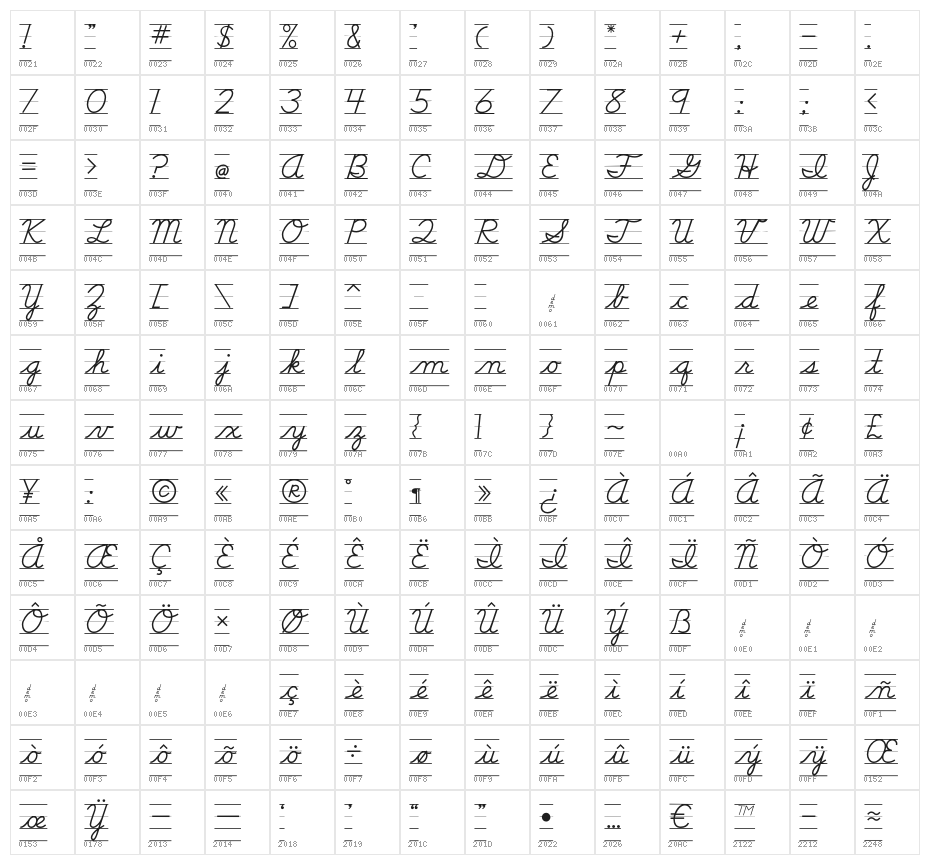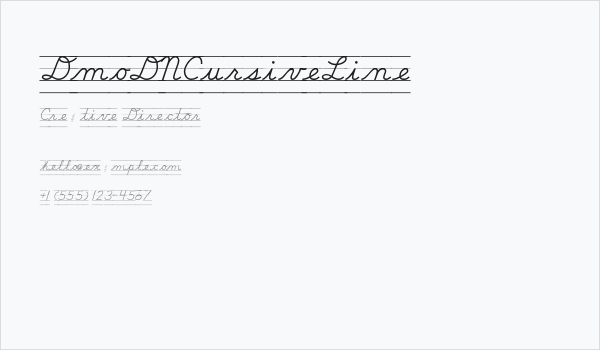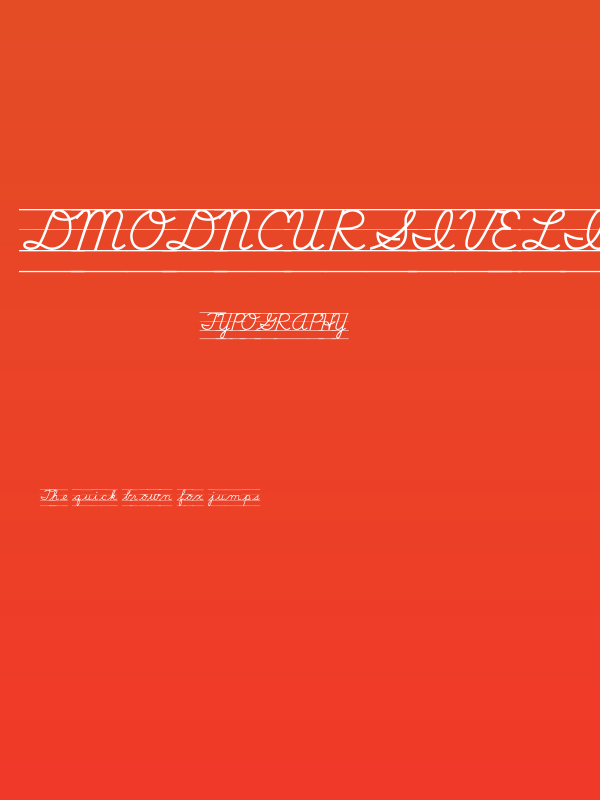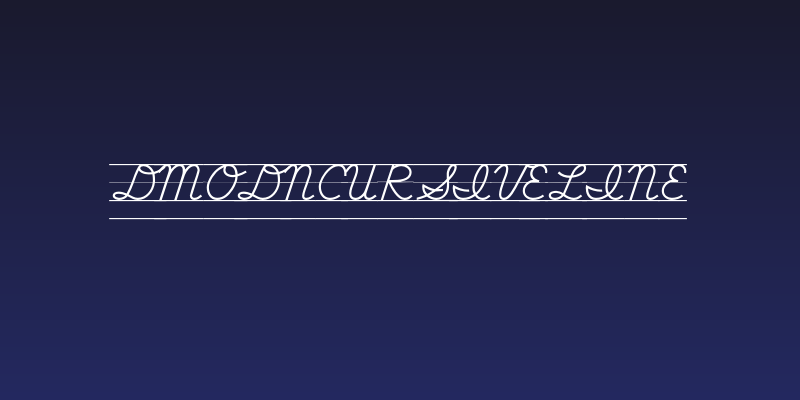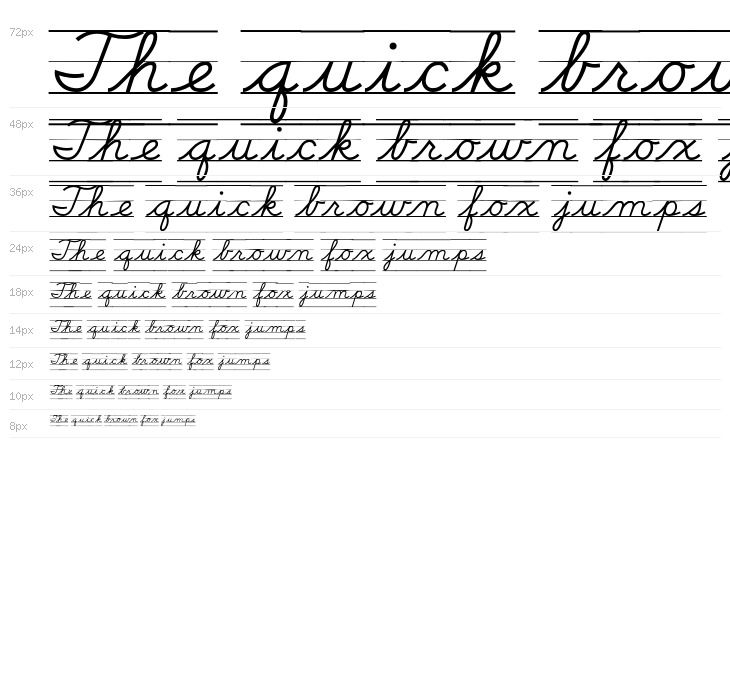
DmoDNCursiveLine Font
| Caso d'uso | Logos, Invitations, Personal Correspondence |
| Progetti proposti | Ideal for wedding invitations, personal letters, greeting cards, and branding materials that require a touch of elegance. |